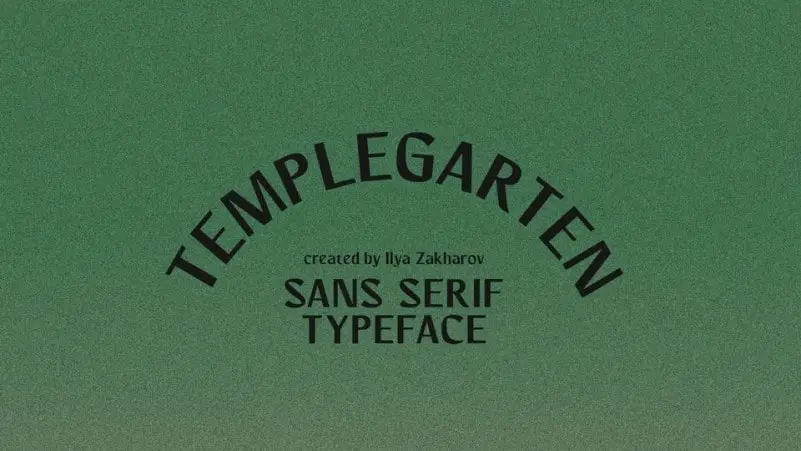
Templegarten Sans Serif Font – Download Grátis
A Templegarten Sans Serif é uma elegante escolha para quem procura um tipo sans serif com um toque gothic. Esta fonte abrange tanto letras maiúsculas quanto minúsculas, números e ainda atende a necessidades internacionais. Ela se destaca por sua simplicidade e modernidade, sendo perfeita tanto para uso textil quanto gráfico. Ideal para aplicativos de jogos, posters, logomarcas, capas de música ou até mesmo roupas, esta fonte é um recurso indispensável em qualquer projeto criativo. O designer Ilya Zakharov capturou a essência do gothic na Templegarten, resultando num tipo que se destacará em qualquer design e proporcionará uma identidade visual única para seus projetos. Com sua utilização simples e eficaz tanto em texto quanto em exibição, esta fonte é uma opção clara para aqueles buscando um estilo moderno e atraente.